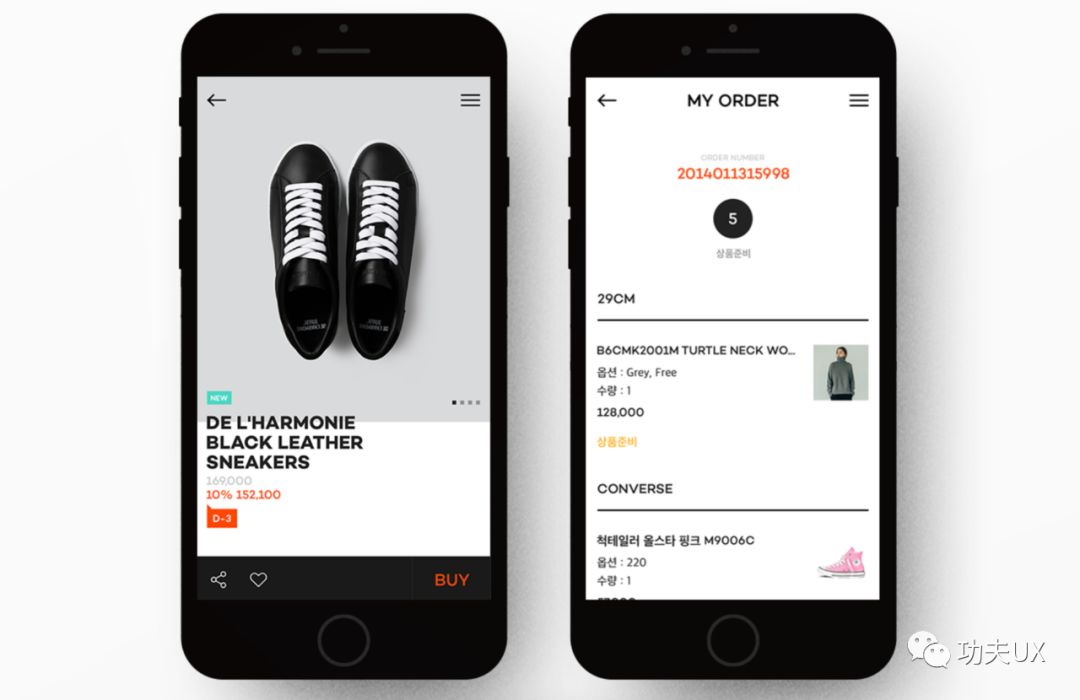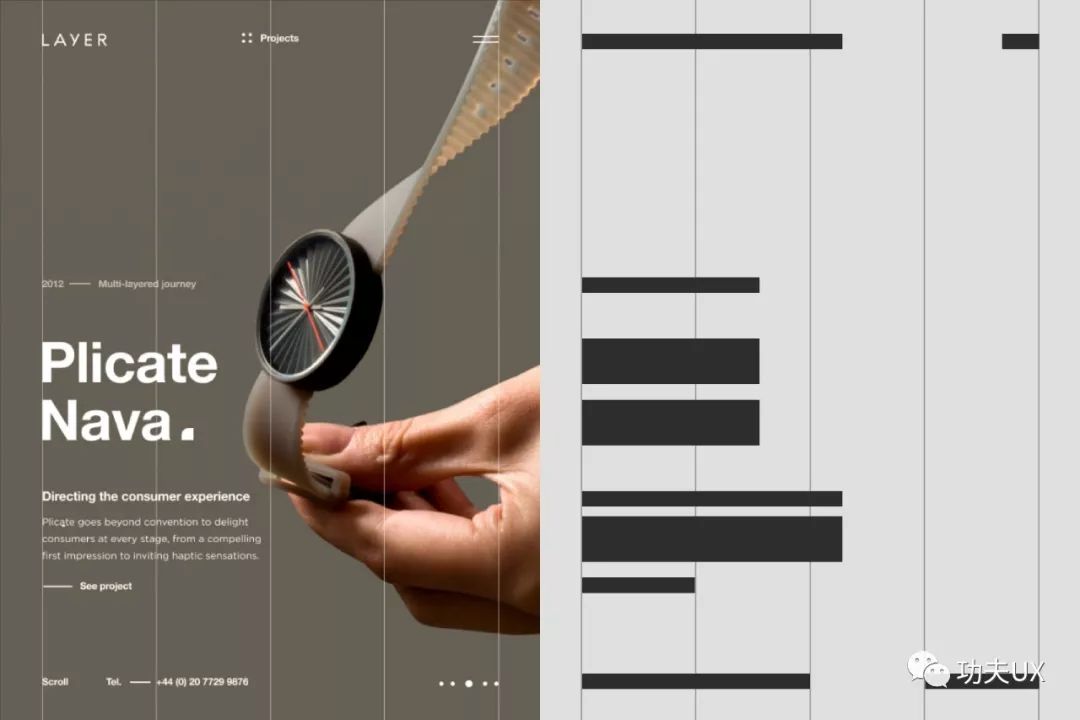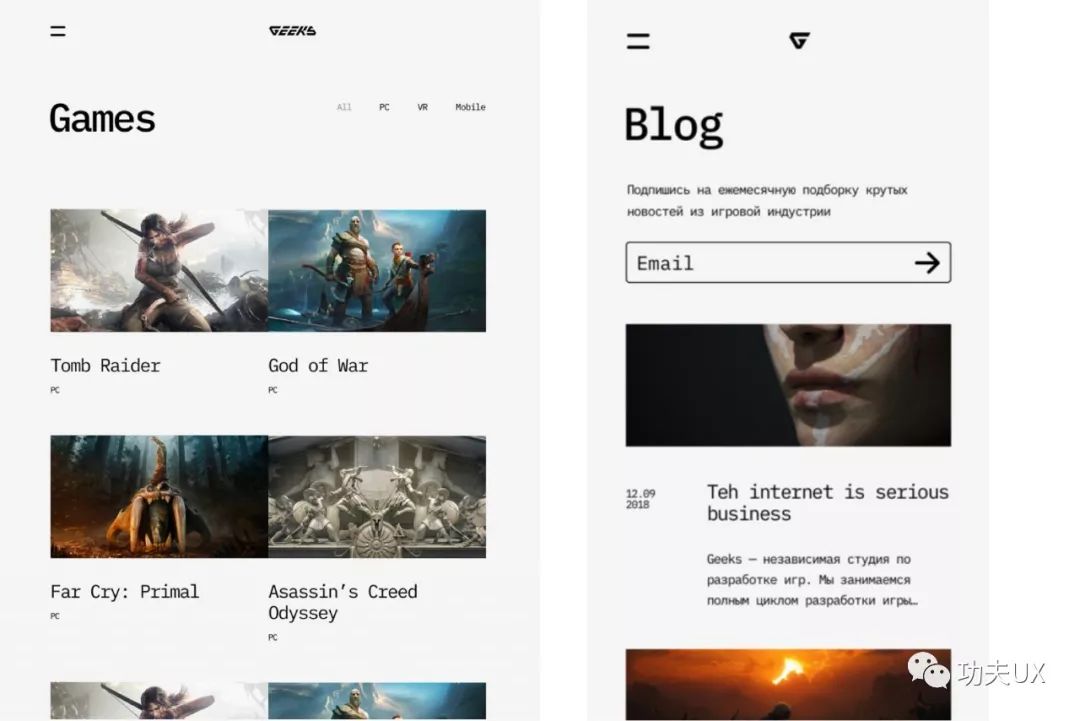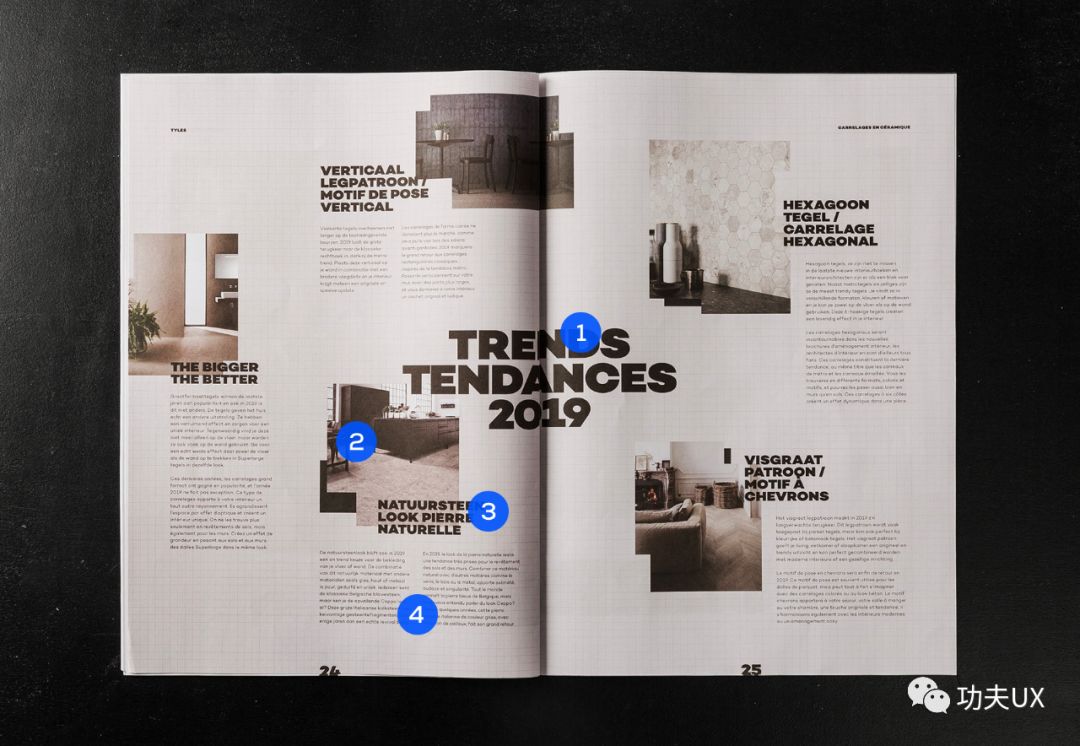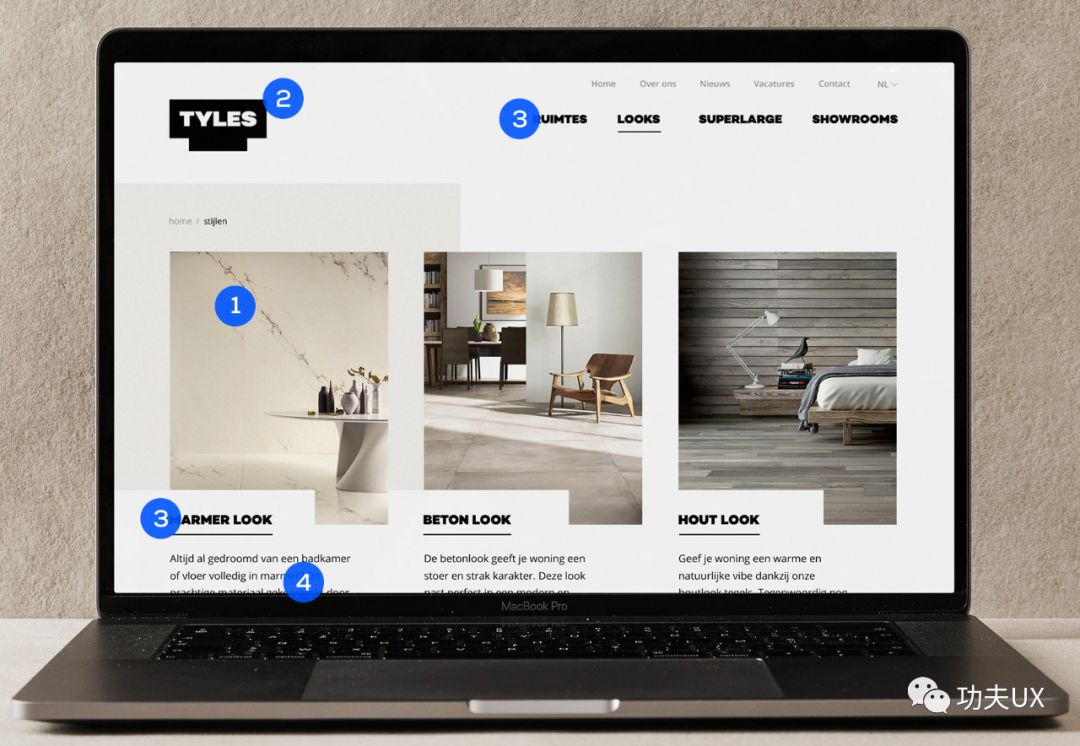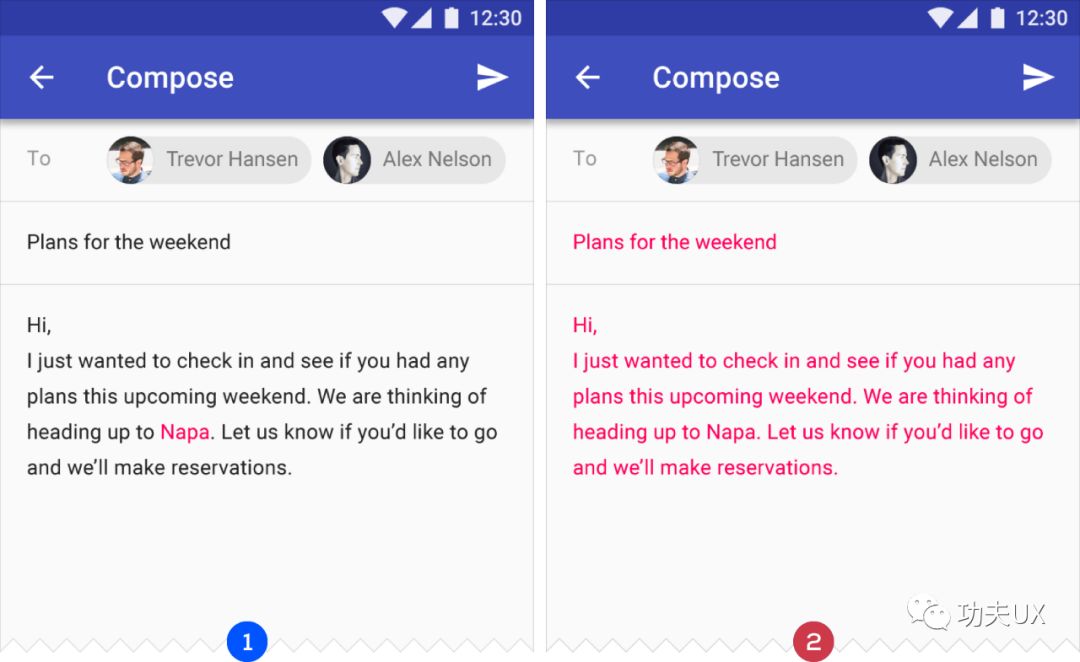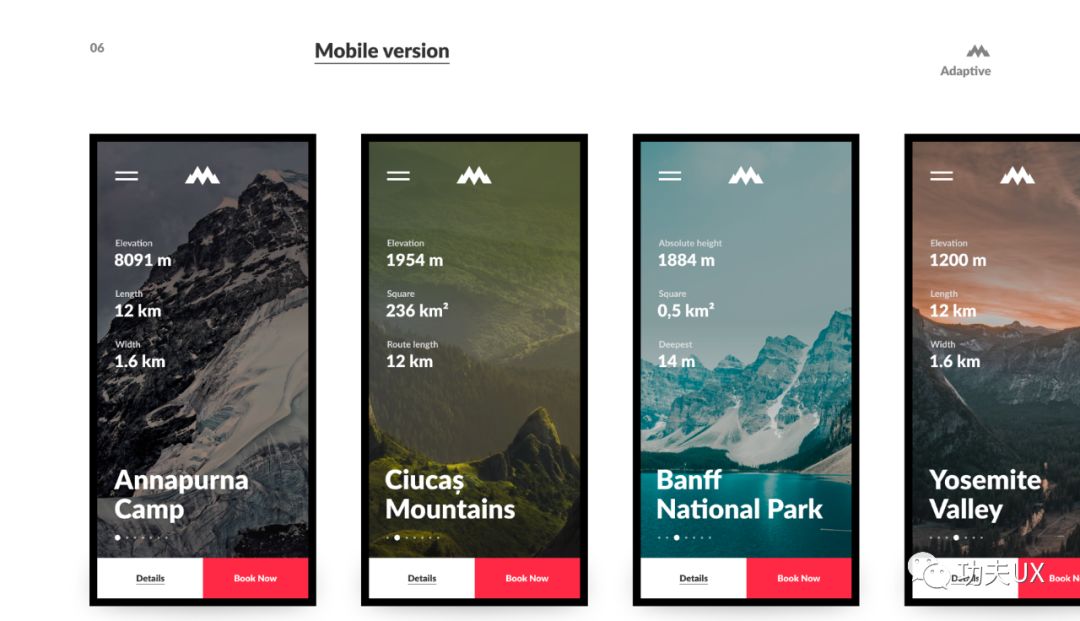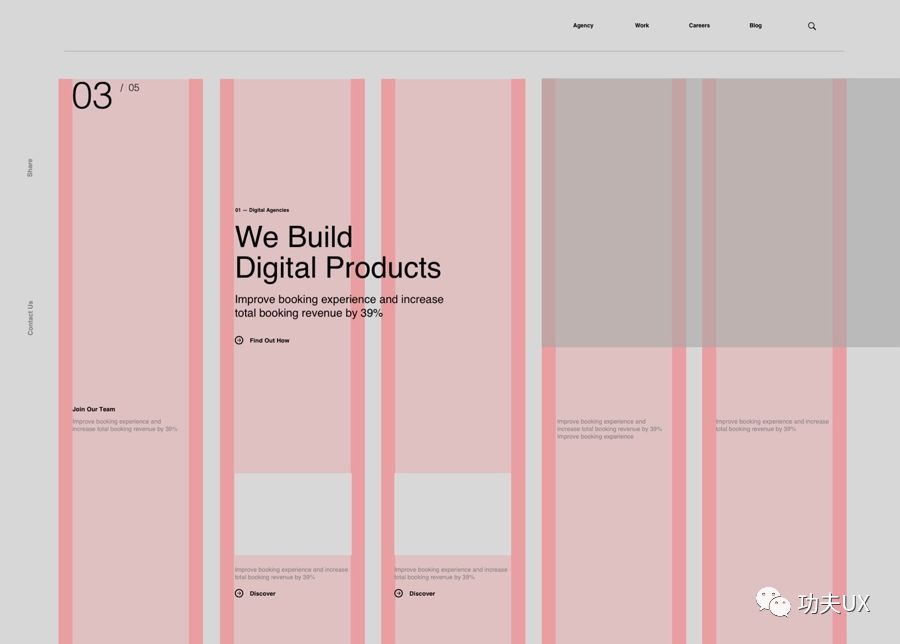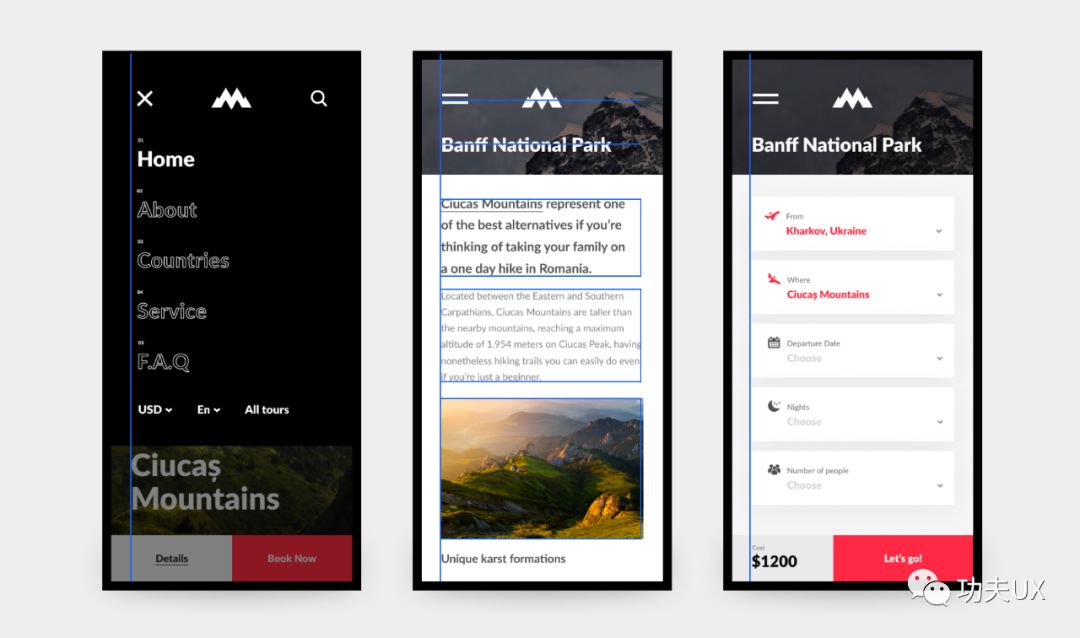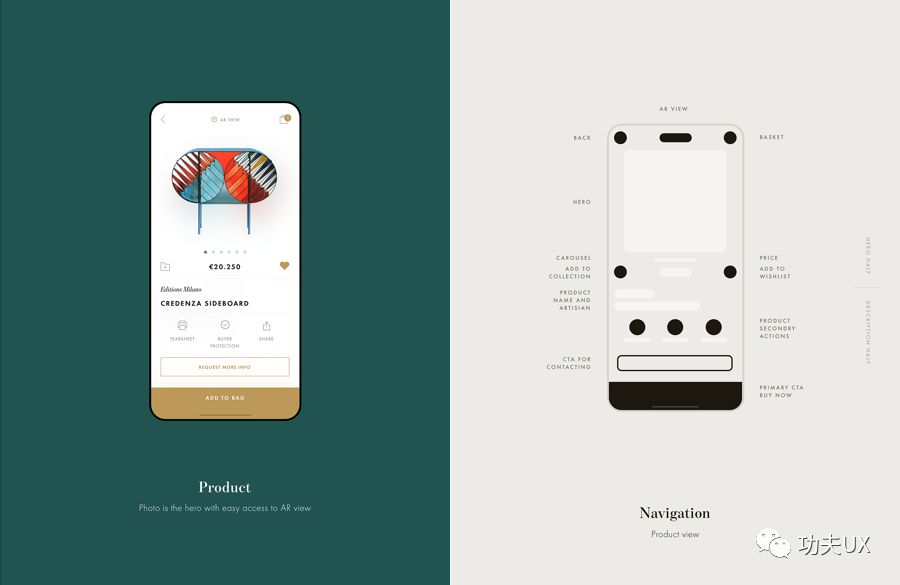
如何创建精致的UI界面?提升设计排版的五种方法
为什么要学习排版
排版是界面设计中最难的部分,也是非常重要的一部分,它以各种形式存在界面中,纯文本排版、图形文排版、图片文本排版等等,这是我们在做设计时候,经常会面临的问题,好的排版能有效地向用户传递关键的信息,同时也能提升产品使用体验。在我们日常生活中,离不开设计排版,包括经常见到的各种广告与电影宣传海报,如果不能让用户在短时间内记住关键信息,这个设计就是失败的。因此我希望通过今天这篇文章,能够让你对排版有一些新认知升级
提升设计排版有哪些方法
在界面设计中,影响排版设计的因素有很多,我总结归纳了7个维度(当然还有其他更细的,在这里就先暂时不讲),它直接影响整个排版质量,这些方法当然不是绝对,但是如果能巧妙综合的运用到界面排版中,能保证大部分界面设计感得以提升,当然也是需要不断刻意练习来提高的。
他们分别是:1,合理运用空间的力量 2,大小的力量 3,论颜色的重要性 4,对齐的力量 5,平衡定律 6,选择好的字体 7,清晰了解设计目标
合理运用空间的力量
空间即我们常说的留白,当设计元素紧紧地聚集在一起时,界面看起来没有重点,因此需要和谐的运用它,空间的变化直接影响产品的性格,小空间和大空间在视觉感受上,两者完全不同,那么我们在界面设计中如何去更好的运用空间来排版?
有一个很好的方法就是可以运用网格去搭建空间,在平面设计中,运用得非常多,那么在用户界面中,同样也可以运用网格去搭建,
下面看一个案例
如上图作者把一个界面分为4Gird,通过搭建好的网格来进行界面中元素排版,右侧是我拆解的图(备注:网格的搭建并没有任何强制性的规定需要搭建多少列,最终的搭建列数需要根据这个产品内容复杂程度去定义的)比如我最近在做车载HMI设计语言,同样也运用了网格,那么我会根据整个车载HMI产品复杂程度去搭建,同时也运用了几种网格配合使用。
上面两个例子,我们可以发现设计师运用了大空间来设计界面,这使得整个界面呼吸感更强,更透气,因为也是娱乐类偏杂文产品,所以设计会偏艺术化一些。
韩国29cm产品是我比较喜欢的一个app,整体设计呼吸感很强,留白空间大,视觉焦点清晰
大小的力量
我们都知道大的物体更吸引眼球,更容易引起我们的注意,那么在设计中,我们一般都会将重要元素放大,突出显示。
a和b哪个更吸引你?答案是a ,因为a类型排版看起来很大,更具有吸引力
上面案例中算是大小方法上运用比较好的,我们可以看出视觉层次非常清晰了,首先我能快速知道哪些重要信息,肯定是封面图,接着左上角logo,然后就是导航和标题了,最后就是针对每个内容块的一些详细文案解释。
简单示例,重要的信息一定要大,次级信息弱化。
论颜色的重要性
颜色在排版设计中起着很大的作用,在一些场景下能起到点睛之笔,又或者为画面带来活力,又或者代表着品牌,当然我们在UI界面中字体颜色一定要慎用,因为不同颜色,含义是不同的。合理恰当运用颜色, 能够瞬间提升设计品质感。
上面这个web设计中,设计师通过红色来强调重要信息,同时也让灰白的画面有了些许不同之处。
对某些文本使用辅助颜色,例如链接文本,图1 使用方式正确。图2将颜色大量使用在正文,严重影响视觉体验
上面两图都在恰当时候使用颜色,比如打开开关按钮,又或者输入文本高亮显示等,右侧只有在选择文本阶段,使用颜色提示
少量颜色能提升界面品质感,在关键的地方使用品牌颜色或者辅助色,其他通过我们前面讲的大小对比和空间来完成整体界面设计
对齐的力量
对齐是界面设计中我们经常提到话题,也是提升界面品质感最重要的一个隐形的力量,也许有时候我们会忽略他。有时候会不经意间就没做好。
对齐的界面比不对齐的要整齐很多,视觉流也符合用户阅读习惯
我们可以借用前面所学的网格来对齐,这样不仅设计有节奏感, 同时画面很整齐美观
界面设计中,可以有三种思路对齐,当然根据业务板块去选择合适的对齐方式,三种对齐方式都有一个隐形的轴(看我标的线),然后围绕这个去排版设计,自然形成一个规则的视觉流
上面案例中作者整体偏左对齐,这样形成以左为中心一个轴展开视觉流走向
平衡定律
我记得在刚入行做设计时候,会常遇到有人说你的设计,要么是这边太重了,要么就是太轻了,或者这边要不加点东西进去,不然太空了,为什么?这就是平衡定律,如果同一个环境下的物体没有保持平衡关系,我们视觉感受上是很不舒服的。下面我们看几个例子
图1和图2我们可以看出图2。给人第一感受就是不平衡的,整体视觉重心偏左了
上图案例,设计师通过按钮来平衡整个画面视觉重心,因为左侧内容多,如果按钮很弱或者很小,是很难平衡画面的,因此我们做界面时候,定义一些按钮大小也是非常考究的
左边视觉界面,右边拆解原型出来,我们可以看到设计师也是通过元素合理分布使得界面整体平衡
选择好的字体
字体选择对界面排版非常至关重要,这也是所有界面排版中必要的一步,不同字体有不同的性格属性,我们需要根据产品来选择恰当的中英文字体,同时,也需要记住,一个产品APP界面设计中,字体最好不要超过两种
推荐一些我认为2019比较好用的英文字体,大家做概念设计时候或者提案方案包装时候是可以用到的哦(吐血推荐)
字体分别是:Montserrat 和 Nexa
字体分别是:Futura 和 Playfair_Display
中文好用的字体,大家应该都知道,平方字体,思源黑体,汉仪旗黑,兰亭纤黑,我就不做示例了。
清晰了解设计目标
终于到最后部分了,最后这点是整个设计排版的核心之一,为什么?如果不清晰设计目标,那么整个排版到最后产出和你用户群体或者产品性格是两种类型的,不同产品风格会有不同的排版类型
比如我们产品是奢侈品,那么整体排版设计风格一定是使用大网格,大空间去设计,字体纤细等。如果是简约现代呢?又或者母婴产品,科技产品,娱乐产品等等,每个会有一些特殊排版思路。所以了解你的设计目标,并确定设计原则。
通过七大点排版思路,可以更好的运用在界面设计中,每个排版原则并不是独立的个体,他们之间是相辅相成的关系,比如大小离不开网格,也离不开对比,颜色等等,缺乏某些元素,那么界面就会缺失灵魂,设计产出质量并不好!好了本期到这里结束,下期会继续和大家分享如何巧妙运用图形提高界面品质感和增强细节!